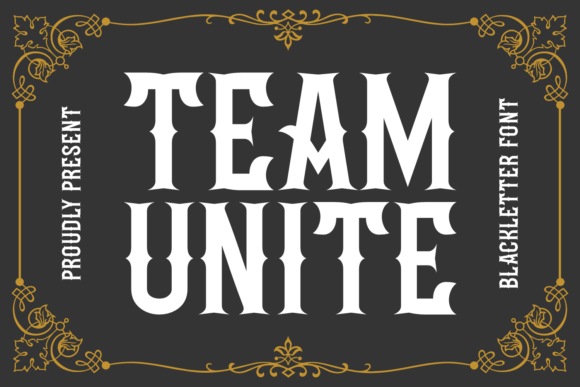
Team Unite
適切なデザイン要素を見つけるのは難しい場合がありますが、Team Uniteは作品を即座に引き立てる優れたコレクションを提供します。
POD(オンデマンド印刷)製品、結婚式の招待状、またはソーシャルメディアのグラフィックを作成している場合でも、Team Uniteは理想的です。
無料の代替品は存在しますが、Team Uniteに見られる商用権と技術的な完璧さが欠けていることがよくあります。